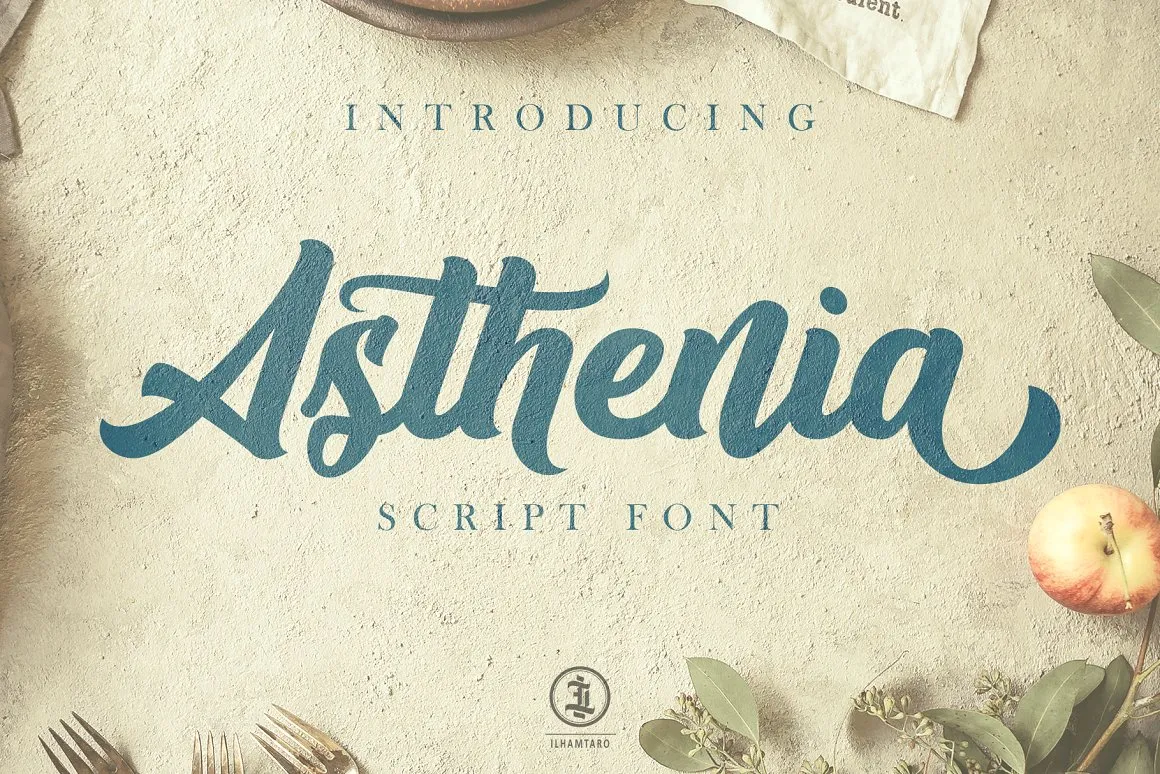
Você receberá a melhor tipografia de nosso catálogo, e fique à vontade para agradecer por sua companhia ao longo dos anos. Introduzimos Asthenia, uma fonte cíntica criada e compartilhada pelo designer ilhamtaro. Inspirada na escrita com báculo, Asthenia destaca-se pela elegância de seus traços fluidos e espessos. Esta fonte cíntica contém 420+ símbolos gráficos, incluindo letras maiúsculas e minúsculas, números, pontuações, ligaduras e muitas alternativas para caracteres. Com esta riqueza de opções, Asthenia torna-se uma fonte ideal para criar logotipos, cartazes, flyers, design de camisetas, embalagens, marca e produtos promocionais, além de projetos criativos de outros tipos.